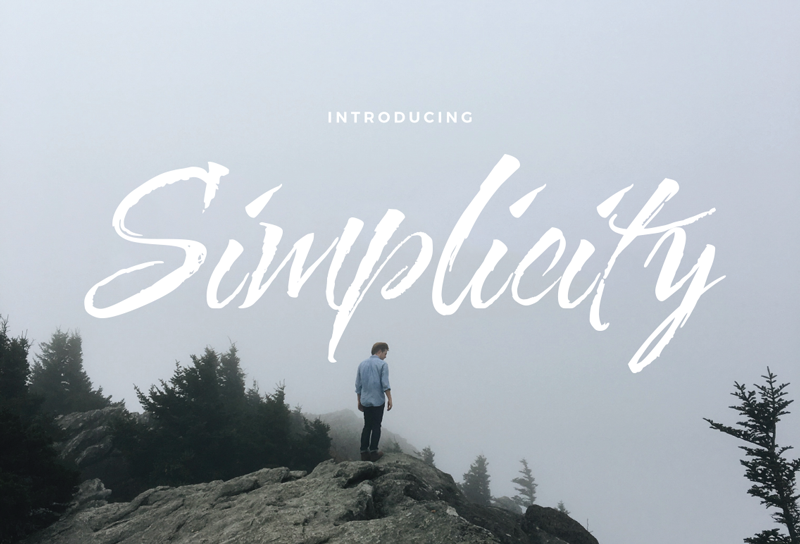
Simplicity Script Font – Download Grátis
A fonte ‘Simplicity Script Font’ é uma elegante escolha para criar mensagens singelas e profissionais. Seu design fluido e harmonioso cria um equilíbrio entre modernidade e sofisticação, tornando-o perfeito para aplicações como nomes de usuários em sites pessoais ou branding minimalista. Ideal para textos legíveis e atraentes, esta fonte mantém os detalhes essenciais do design script, permitindo que você expressa seu estilo de maneira única. Em um mundo repleto de recursos gráficos digitais, a ‘Simplicity Script Font’ oferece uma solução versátil para designers e criativos, combinando facilidade de uso com um design sofisticado que impressionará seus leitores.